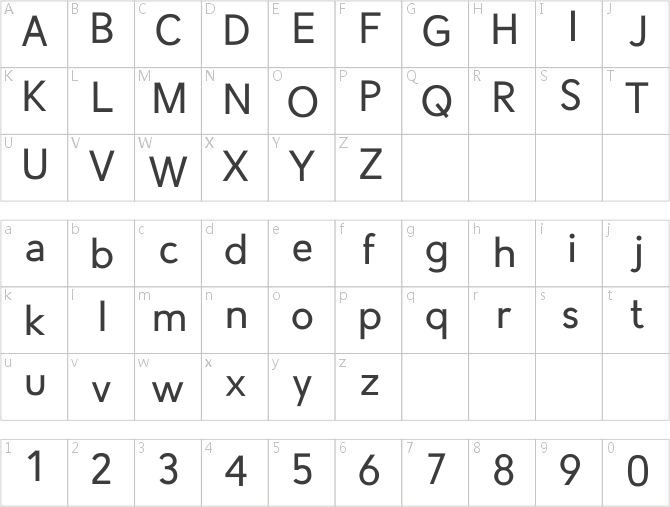
Crescent-Regular 詳情頁
字體名稱: Crescen
Crescent-Regular
Crescent-Regular介紹
Crescent-Regular字體字庫是一款讓人賞心悅目、百看不厭的英文字體,適合各類廣告和產品包裝設計應用,字體大小0.01MB,格式為ttf字體,上傳用戶是后天的昨天,作者/版權方為未知